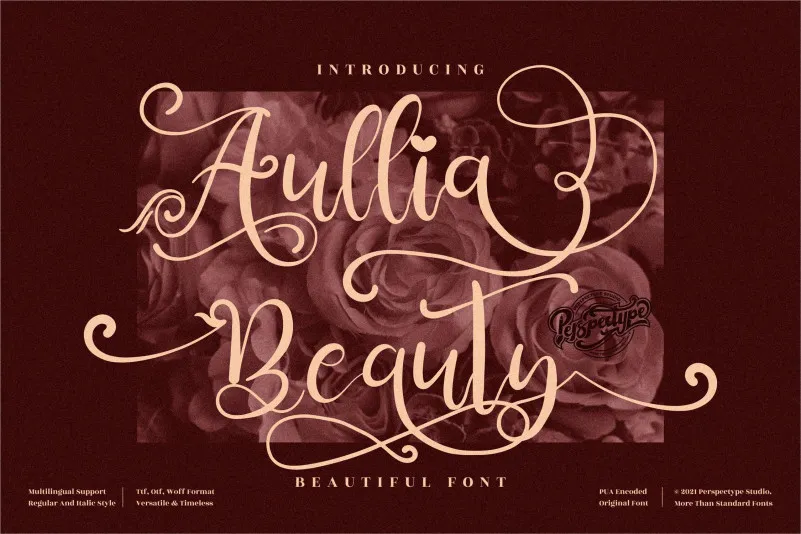
Esta é uma linda e refinada fonte script. Ideal para criar identidades e marcas elegantes e modernas, esta fonte pode ser usada em diversos projetos, desde logos até materiais de wedding e posts nas redes sociais. Suas linhas são fluidas e detalhadamente elaboradas, tornando-a perfeita para design personalizado e criativo. A Aullia Beauty Font é ideal para designers que buscam uma fonte com um visual sofisticado e atual, capaz de agregar valor em qualquer projeto. Com seu suporte ao PUA, pode ser facilmente acessada e manipulada, permitindo a inclusão de todos os símbolos e desenhos especiais que tornam esta fonte tão versátil. Seja para um evento especial ou uma publicação no Instagram, Aullia Beauty é uma escolha perfeita. Sua elegância moderna garante que suas criações fiquem atraentes e imprimíveis em qualquer plataforma digital ou impressão.